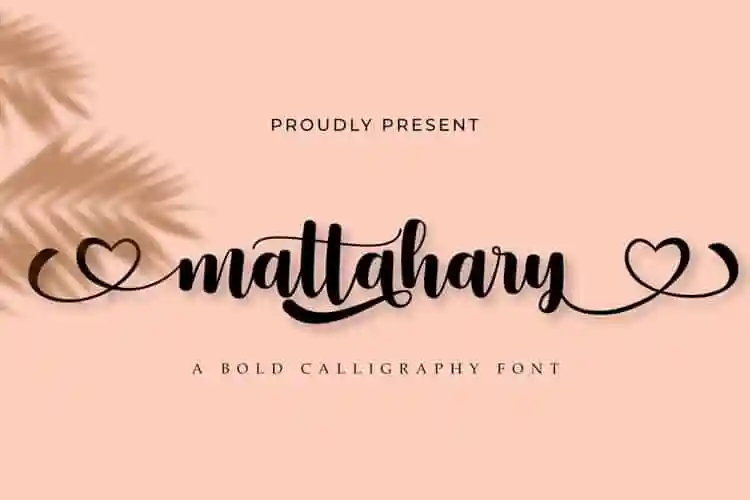
Mattahary Calligraphy Font – Download Grátis
A fonte “Mattahary Calligraphy Font” é uma combinação suave e ousada de estilo vintage e script, ideal para diversos projetos gráficos. Essa elegante fonte foi criada por Madatype Studio e inspirada nos padrões tipográficos clássicos, trazendo ao seu design um toque único e vibrante. Perfeita para aplicações em logotipos, convites de casamento, camisetas, cartas de papelaria, adesivos, notícias, materiais publicitários e identidades visuais, entre outros. Com suas possibilidades variadas, seja ela para web, impressão ou animação, a “Mattahary” trará resultados impressionantes em qualquer projeto. Suas formas suaves e dinâmicas são especialmente adequadas para headlines de todas as proporções, bem como blocos de texto que permitem variações desde o máximo até o mínimo. É uma fonte ideal para quem busca uma mistura suave de elegância e originalidade para seus projetos gráficos.